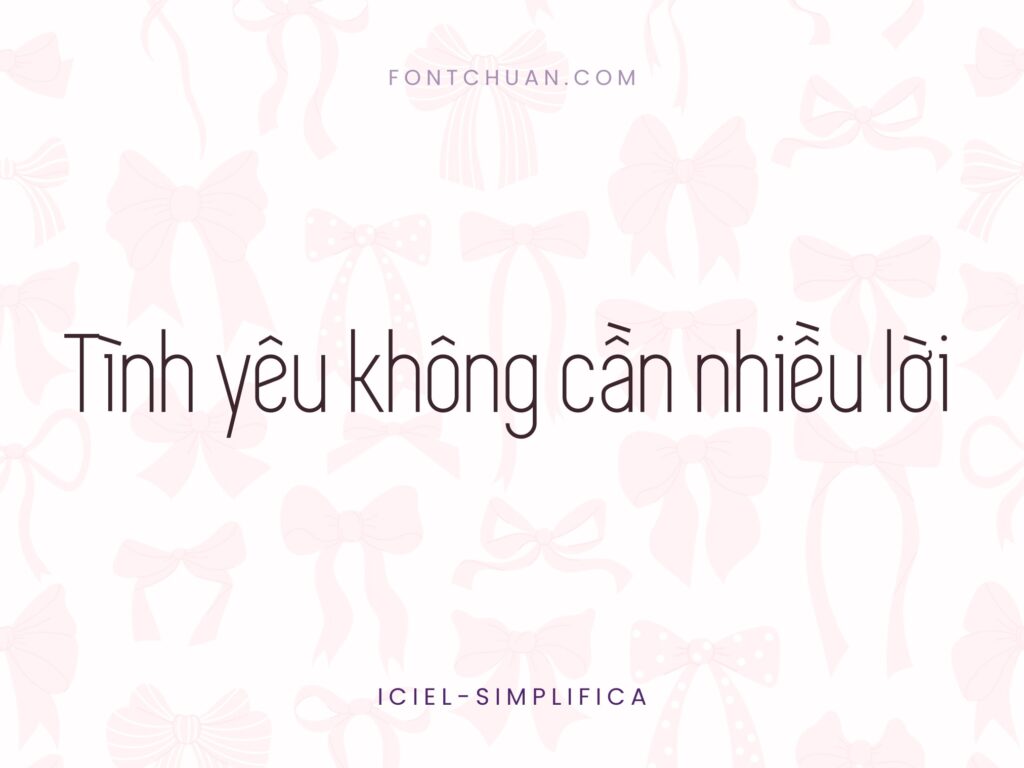
Font iCiel Simplifica Việt Hóa
Simplifica là một kiểu chữ sans-serif mảnh mai, được thiết kế bởi KAIWA. Font này có thiết kế đơn giản, hiện đại với các đường nét đồng nhất và chiều cao chữ cái lớn, giúp tăng cường khả năng đọc. Đặc biệt, Simplifica đã được Việt hóa bởi iCiel, hỗ trợ tiếng Việt cùng nhiều ngôn ngữ khác, đáp ứng nhu cầu đa dạng của người dùng. Thành viên của Font Chuẩn đã sưu tầm và chia sẻ font này, giúp cộng đồng thiết kế ứng dụng dễ dàng trong các dự án của mình.
Về đặc điểm thiết kế, Simplifica sở hữu các ký tự thanh mảnh, gọn gàng và cân đối, tạo nên sự tinh tế và dễ chịu cho mắt. Font này phù hợp cho các thiết kế như tiêu đề, văn bản dài, giao diện người dùng và các ấn phẩm truyền thông cần sự rõ ràng và hiện đại. Ngoài ra, Simplifica còn thích hợp cho các ngành nghề như quảng cáo, công nghệ, giáo dục và bất động sản, cùng các sự kiện đặc biệt như lễ hội, sinh nhật, Halloween và Trung thu.